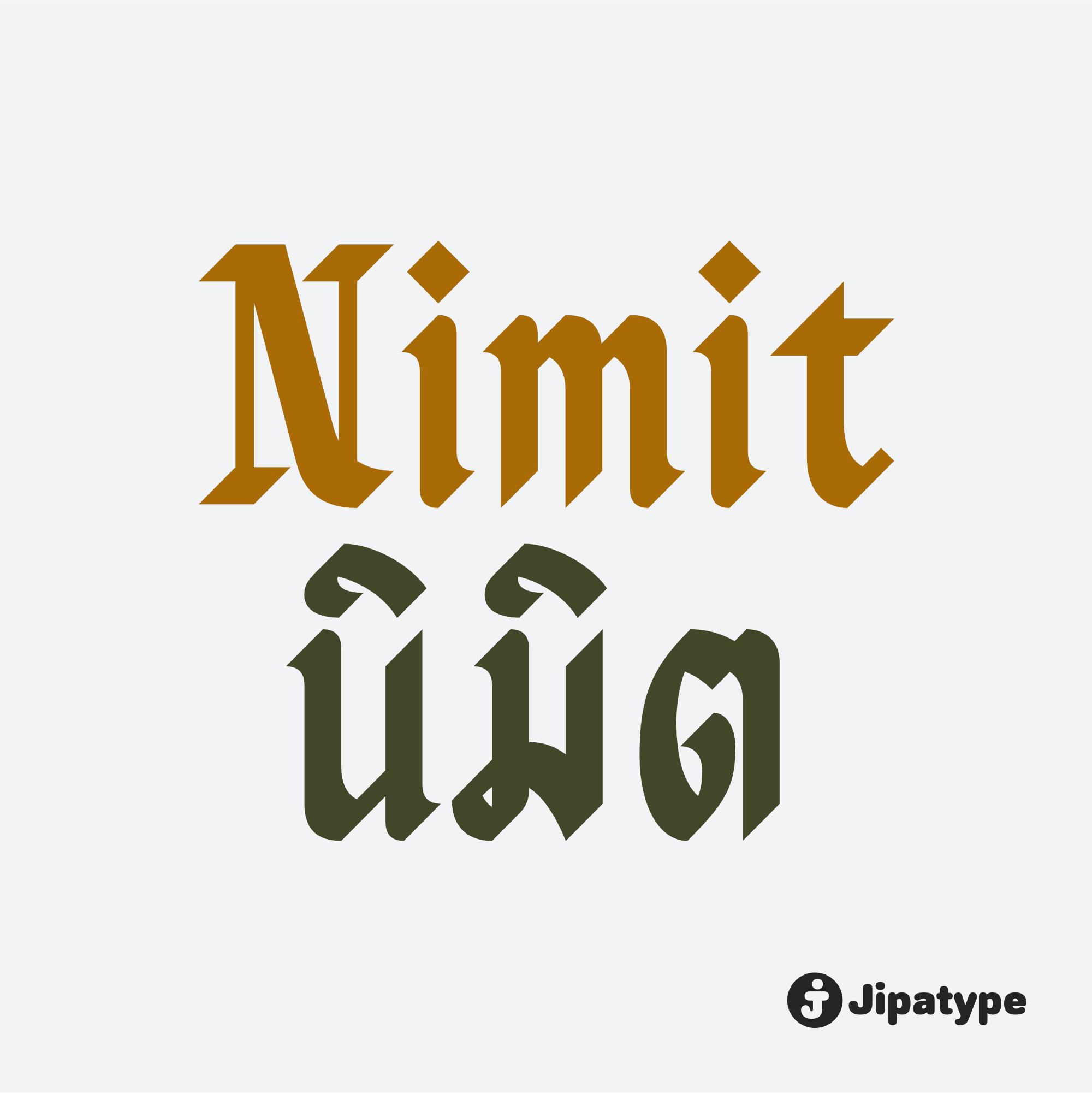
นิมิต | Nimit
ชื่อฟอนต์ : นิมิต | Nimit
นิมิต เป็นแบบอักษรที่เลียนแบบสไตล์การเขียนด้วยปากกาหัวตัด เพื่อให้ลักษณะตัวอักษรออกมาเป็นอักษรวิจิตร เหมาะสำหรับสื่อประชาสัมพันธ์ที่การสื่อถึงความเก่าแก่ มีมนต์ขลัง แบบอักษรนี้ประกอบด้วย 7 รูปแบบ ครอบคลุมน้ำหนักเส้นตั้งแต่บางที่สุดจนถึงหนาที่สุด โดยรองรับทั้งชุดอักษรลาติน 1 และอักษรไทย
Creator : อานุภาพ ใจชำนาญ (Anupap Jaichumnan)